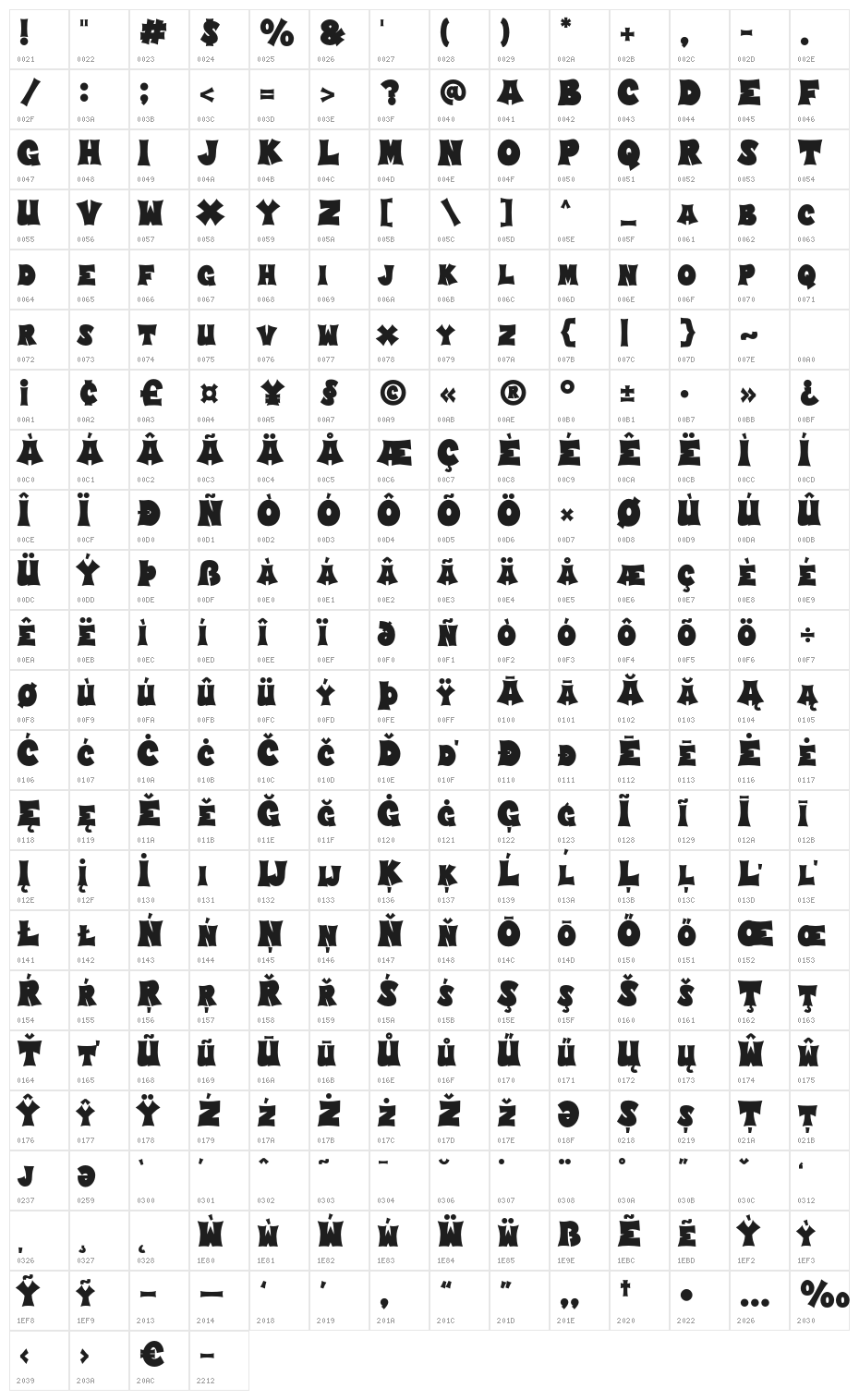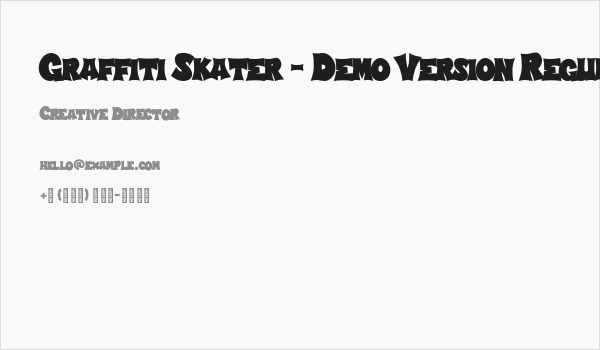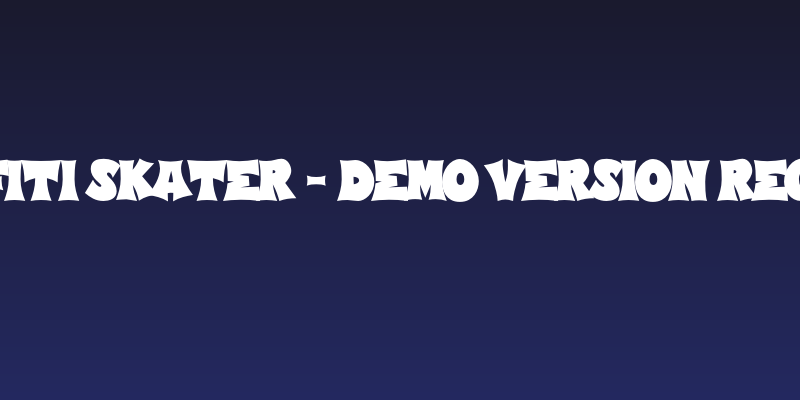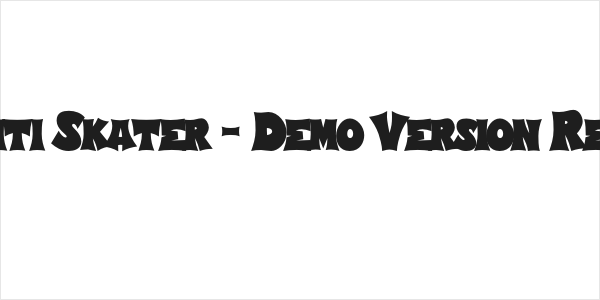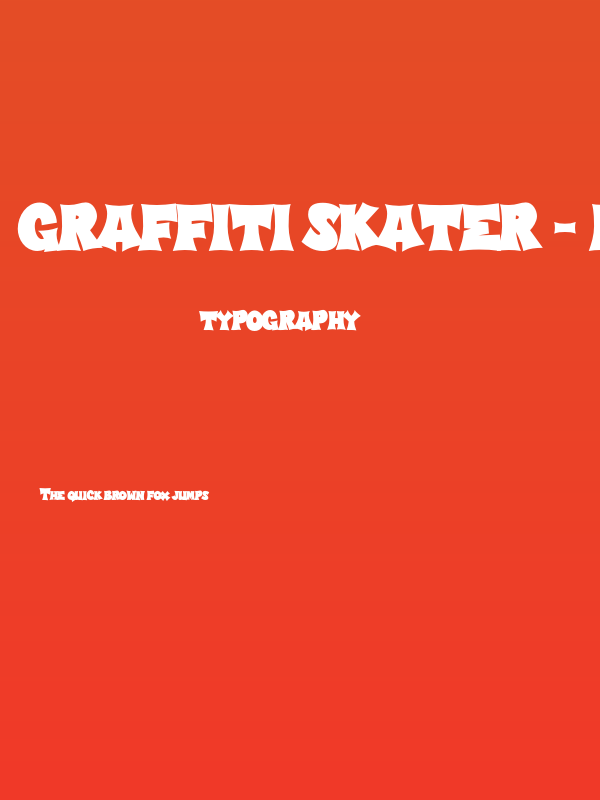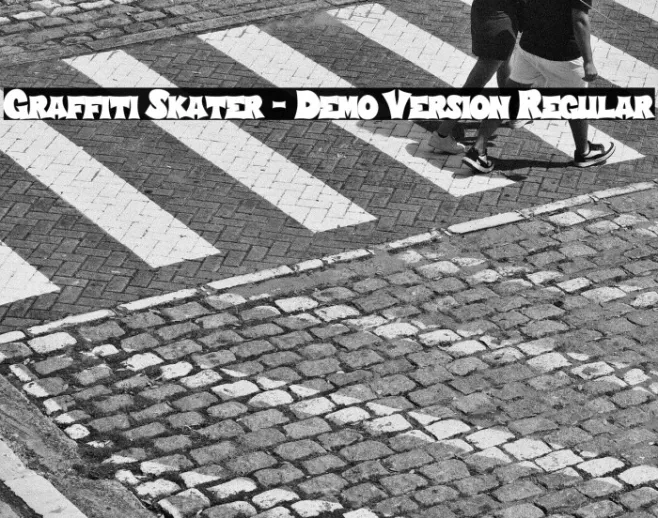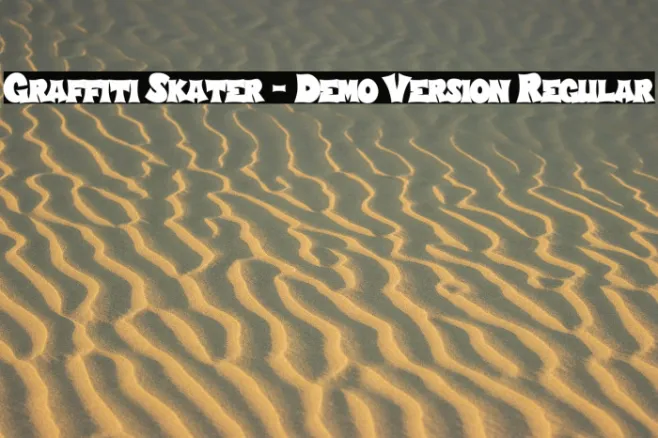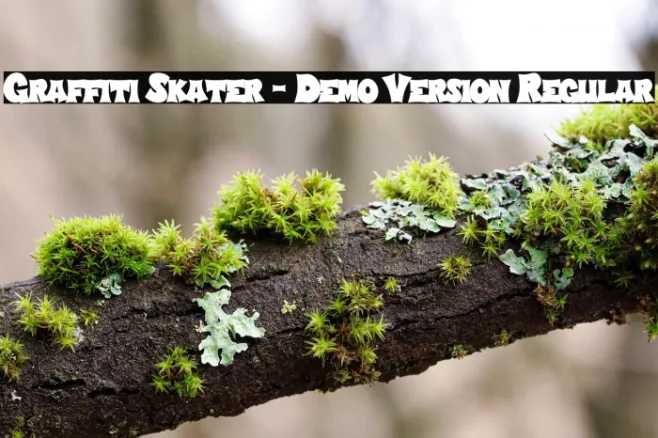
Graffiti Skater - Demo Version Regular Font
| Gesamtstil | Urban, Rebellious, Energetic |
| Anwendungsfall | Logos, Posters, Headlines |
| Vorgeschlagene Projekte | Ideal for urban-themed designs, skateboarding event posters, streetwear branding, and music album covers. |